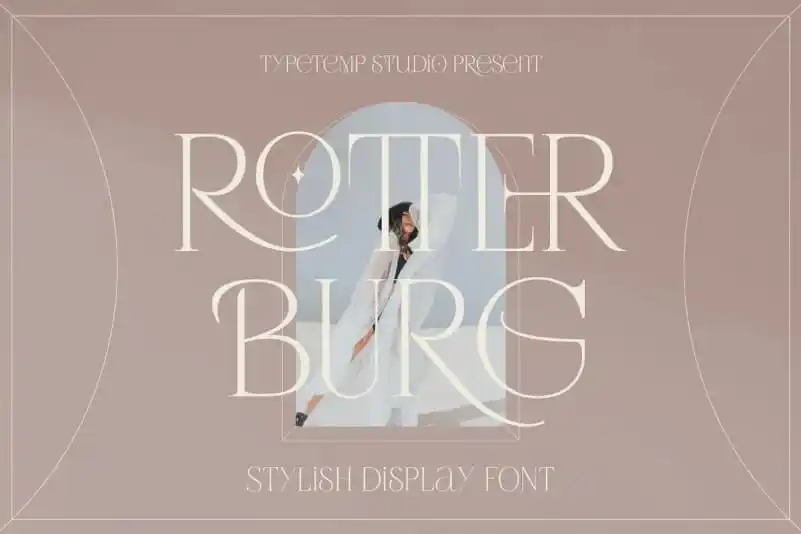
Rotterburg Serif Font – Download Grátis
A Rotterburg Serif Font é uma fonte serif moderna e sofisticada que se inspira nos estilos dos anos 20, quando as letras serif eram usadas com frequência no design gráfico. Essa elegante fonte mantém a elegância de um estilo clássico enquanto incorpora elementos contemporâneos para oferecer uma experiência moderna e acessível. Com seu conjunto abrangente de alternativas de letras e ligaduras, os designers podem explorar diferentes opções de visualização para criar ambientes digitais atraentes. A Rotterburg Serif Font permite aos criativos selecionarem as letras que mais lhes agrada para obter um tipo de exibição personalizado. Esta fonte é uma ótima escolha para quem busca uma combinação perfeita entre os clássicos e o moderno, oferecendo um leque infinito de possibilidades de design.